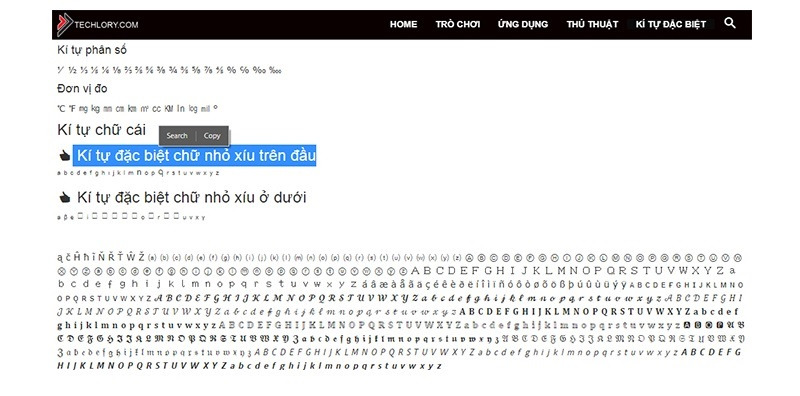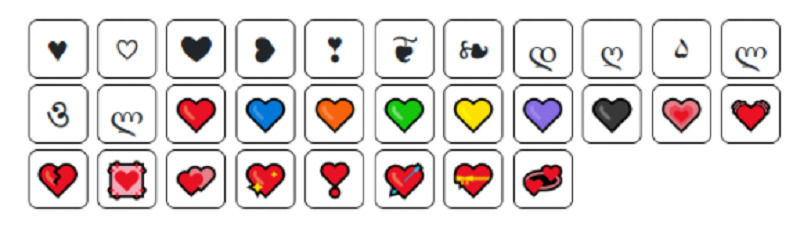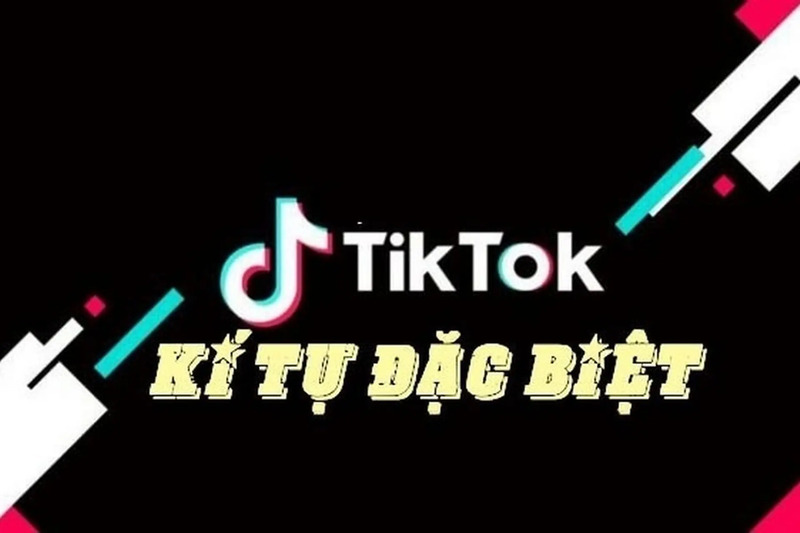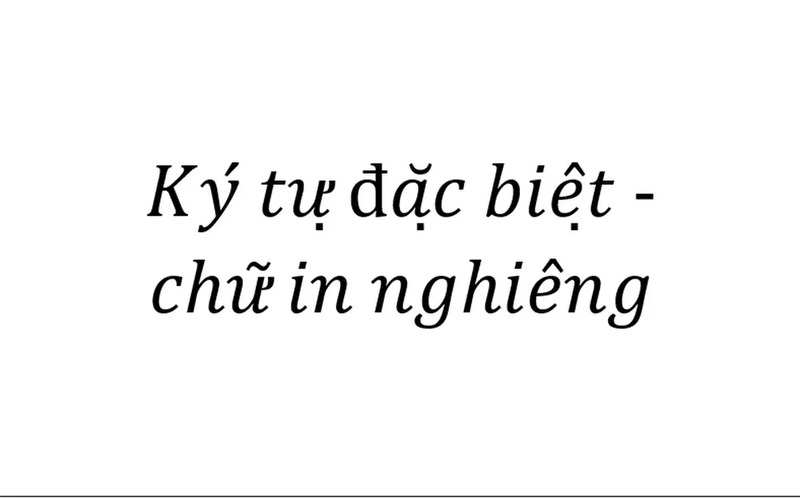
+1001 Kí tự đặc biệt TikTok đẹp, in đậm, chữ nhỏ, trong suốt, in nghiêng, ấn tượng
Kí tự đặc biệt TikTok đang trở thành một xu hướng nổi bật, giúp người dùng tạo ra những cái tên và bio thật độc đáo, thu hút sự chú ý. Xem chi tiết ngay tại đây!
Kí tự đặc biệt TikTok đang trở thành xu hướng hot nhất để tạo ra những tên người dùng độc đáo và thu hút trên nền tảng TikTok. Bài viết sau của Mobifonts sẽ cung cấp cho bạn bộ sưu tập hơn 1001 kí tự đặc biệt TikTok đa dạng, bao gồm: mẫu kí tự đặc biệt đẹp, kí tự chữ in đậm, bộ kí tự chữ nhỏ tinh tế, kí tự tạo tên trong suốt độc đáo, kí tự chữ in nghiêng ấn tượng, tổng hợp kí tự đặc biệt theo chủ đề (trái tim, trái cây, con vật, bông hoa), cùng với hướng dẫn sử dụng và câu hỏi thường gặp.
Hãy cùng khám phá để tìm ra những kí tự đặc biệt TikTok phù hợp nhất cho trang cá nhân của bạn!
Mẫu kí tự đặc biệt TikTok đẹp bao gồm những ký tự unicode độc đáo giúp tạo ra tên người dùng thu hút và dễ nhớ. Phần này sẽ giới thiệu các loại kí tự cơ bản, kí tự trang trí và kí tự emoji phổ biến nhất. Tên kí tự đặc biệt TikTok được chia thành nhiều nhóm khác nhau để bạn dễ dàng lựa chọn. Những kí tự dưới đây không chỉ đẹp mắt mà còn tương thích với hệ thống TikTok.
Kí tự đặc biệt TikTok chữ in đậm là một trong những lựa chọn phổ biến nhất để tạo ra tên TikTok mạnh mẽ và thu hút. Phần này sẽ hướng dẫn cách sử dụng font chữ in đậm unicode, các công cụ tạo chữ in đậm và mẹo kết hợp với kí tự trang trí. Kí tự đặc biệt TikTok chữ in đậm sử dụng bộ font Mathematical Bold để tạo ra hiệu ứng chữ đậm tự nhiên. Dưới đây là những kí tự phổ biến như:
Kí tự đặc biệt TikTok chữ nhỏ mang lại vẻ tinh tế và nhẹ nhàng cho tên người dùng TikTok. Phần này sẽ giới thiệu các loại chữ nhỏ chữ trên, chữ dưới và chữ in hoa nhỏ để tạo hiệu ứng độc đáo. Kí tự đặc biệt TikTok chữ nhỏ thường được sử dụng để tạo ra những tên dễ thương và nữ tính. Cùng tham khảo những kí tự đặc biệt phù hợp với tên tiktok hay cho nữ dưới đây:
Kí tự đặc biệt TikTok cho phép tạo tên tiktok trong suốt là một kỹ thuật độc đáo sử dụng các kí tự không hiển thị hoặc kí tự có độ mờ đặc biệt. Phần này sẽ hướng dẫn cách sử dụng kí tự ẩn, kí tự độ rộng bằng 0 và các kỹ thuật tạo hiệu ứng trong suốt. Xem chi tiết các kí tự ngay dưới đây:
Kí tự đặc biệt TikTok dạng chữ in nghiêng mang lại vẻ thanh lịch và phong cách cho tên người dùng. Phần này sẽ giới thiệu các loại phông chữ nghiêng, kí hiệu toán học kiểu nghiêng và cách kết hợp để tạo ra tên TikTok ấn tượng. Để nắm chi tiết về các kí tự, bạn hãy xem ngay thông tin dưới đây: